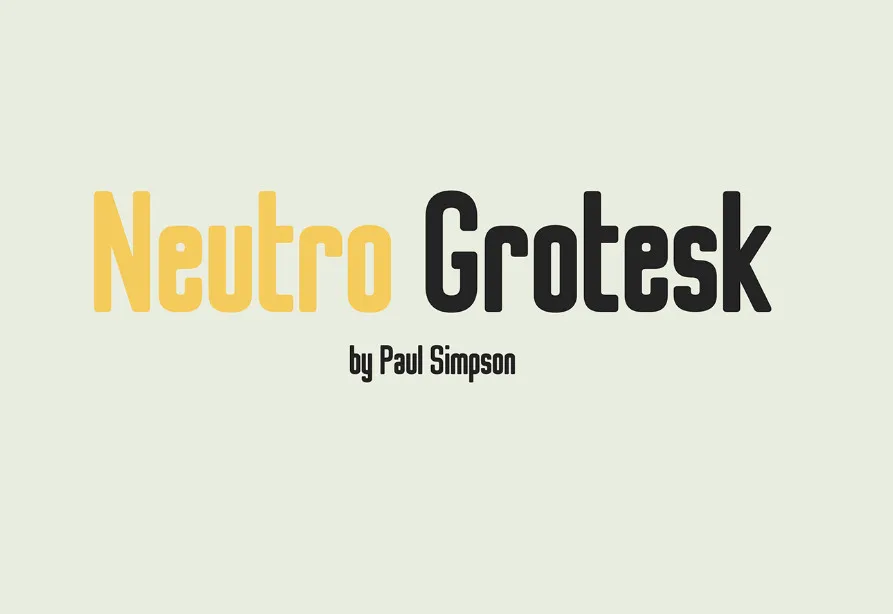
Neutro Grotesk Typeface – Fonte Grátis
Neutro Grotesk Typeface
Esse é Neutro Grotesk Typeface, uma nova tipografia sans-serif lançada pela Hamilton para quem aprecia uma combinação de modernismo e post-modernismo. Inspirada no logotipo Merz dos anos 1920 criado pelo artista russo El Lissitzky, que trabalhava com Kurt Schwitters como cartaz do Dadaismo alemão, Neutro Grotesk transmite uma sensação de simplicidade e funcionalidade clássicas, mas também incorpora um toque pessoal único. Desenvolvido por Paul Simpson, essa tipografia é um exemplo perfeito da evolução criativa que pode surgir a partir de inspirações artísticas passadas. Com 96 caracteres capazes de atender às necessidades de uso tanto para letras maiúsculas e minúsculas quanto números, sinais e pontuação, Neutro Grotesk também foi projetada como um tipo para exposição. Para garantir a melhor legibilidade, é recomendado usar o tipo em tamanho fonte de 24 pontos ou maior.